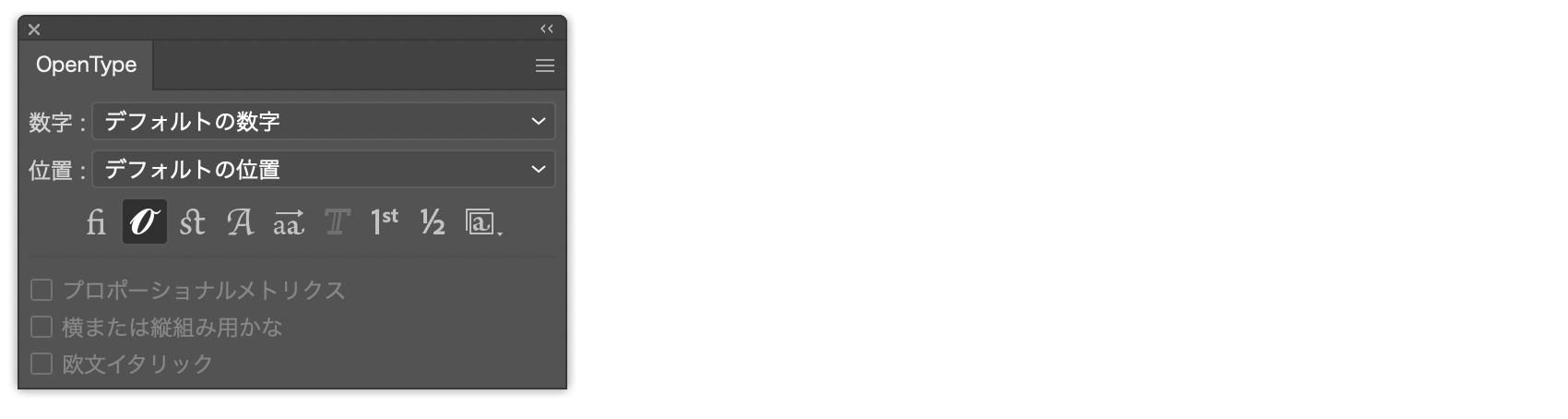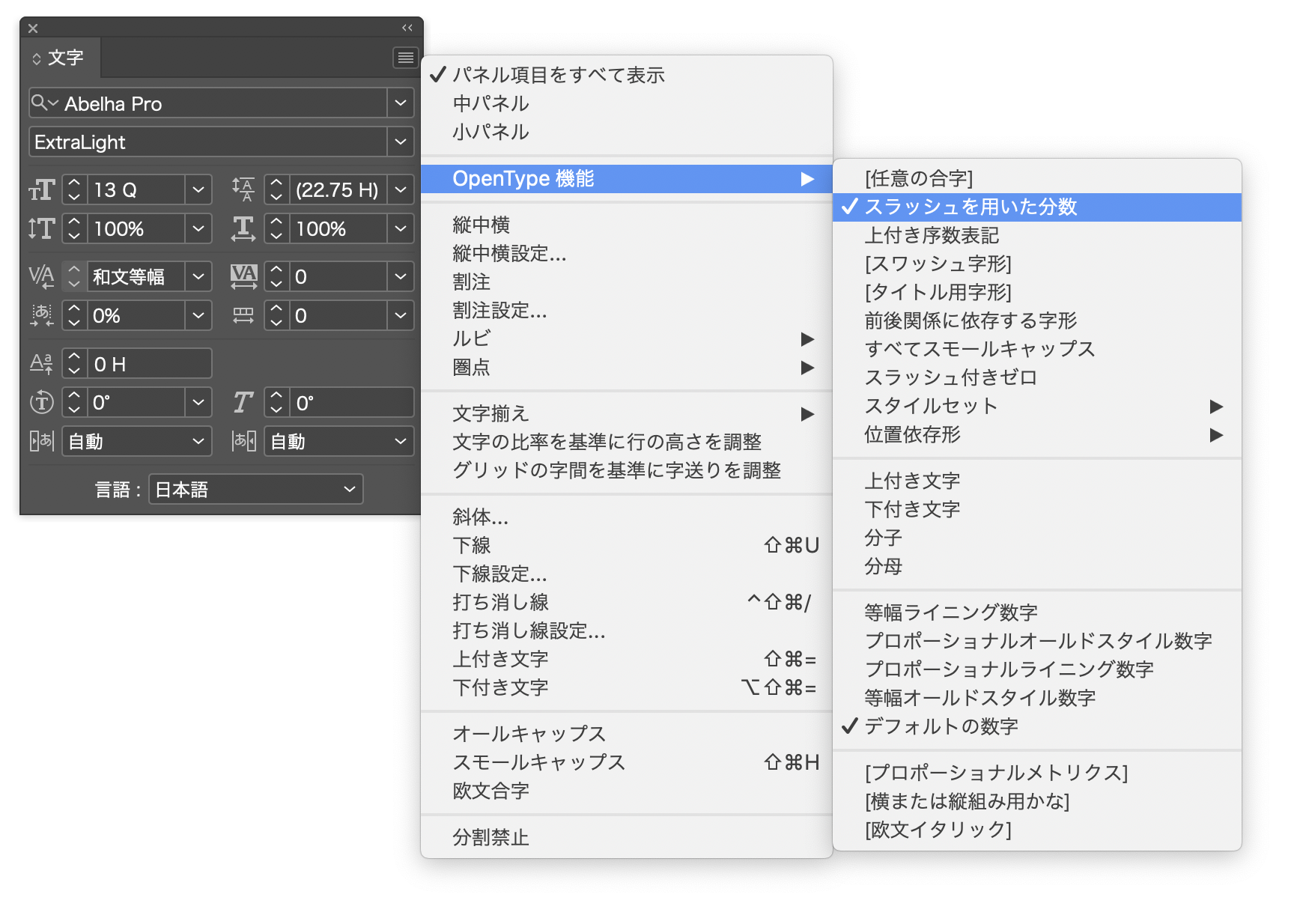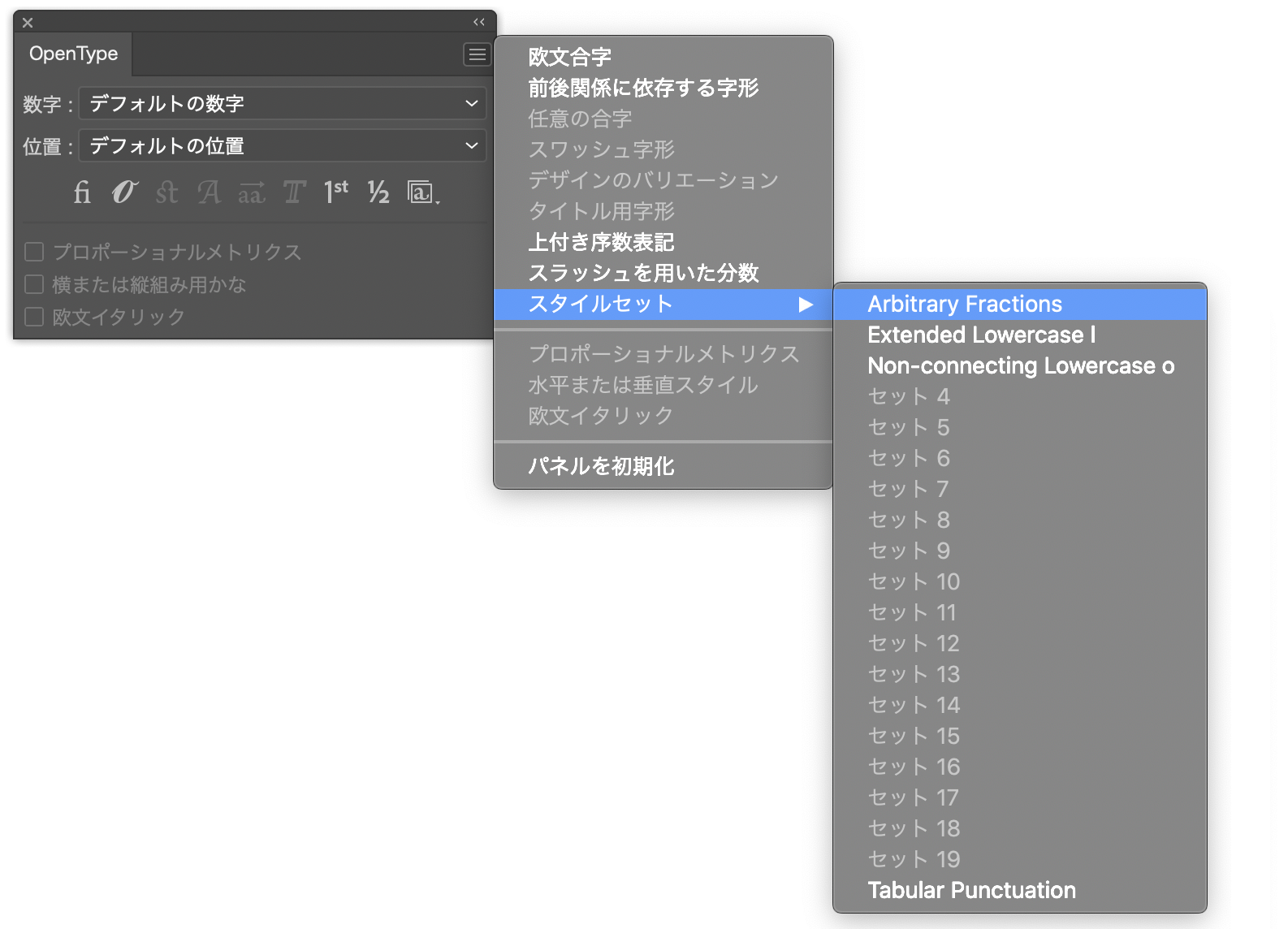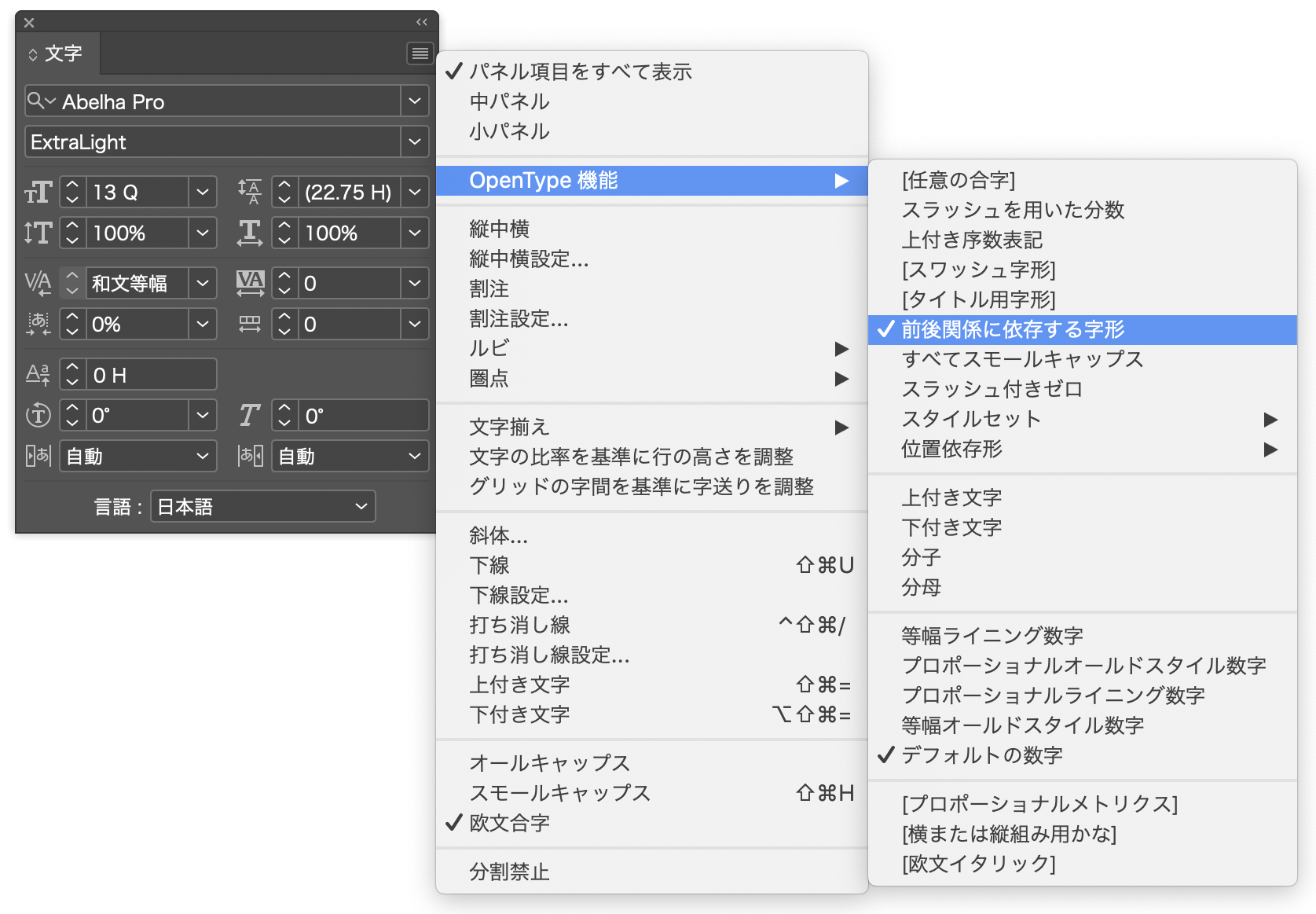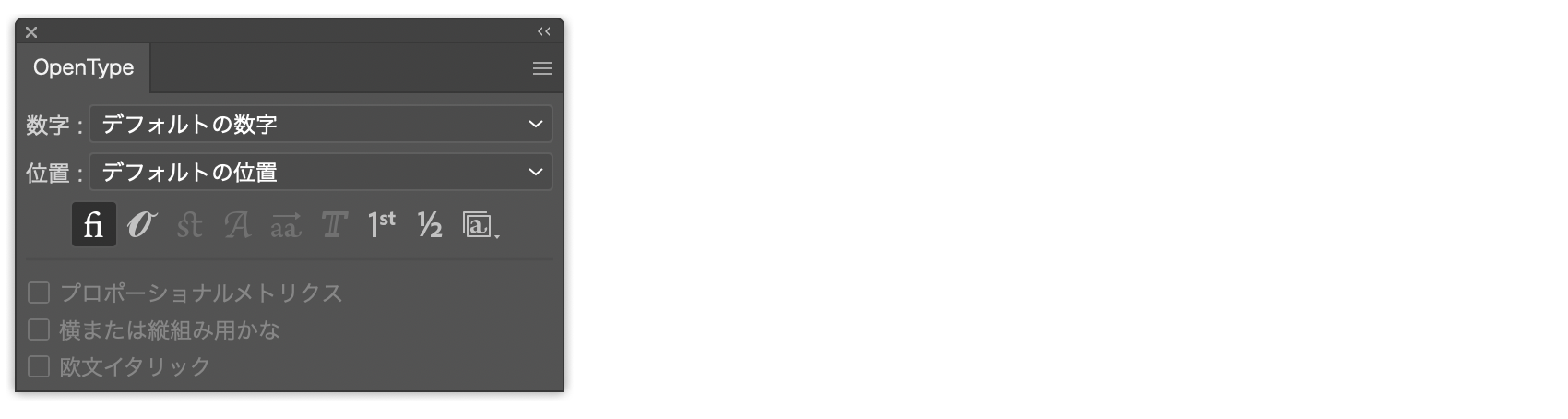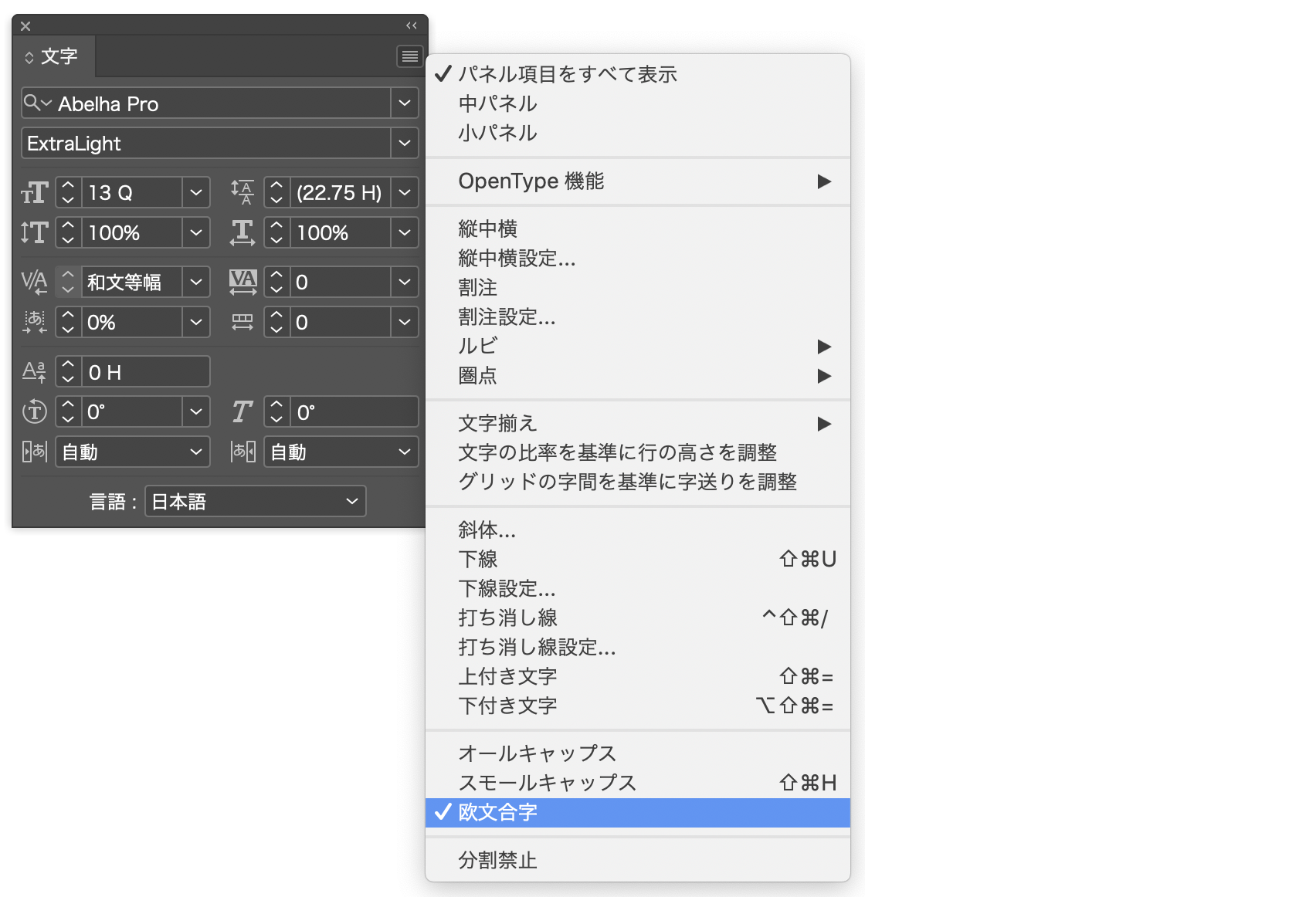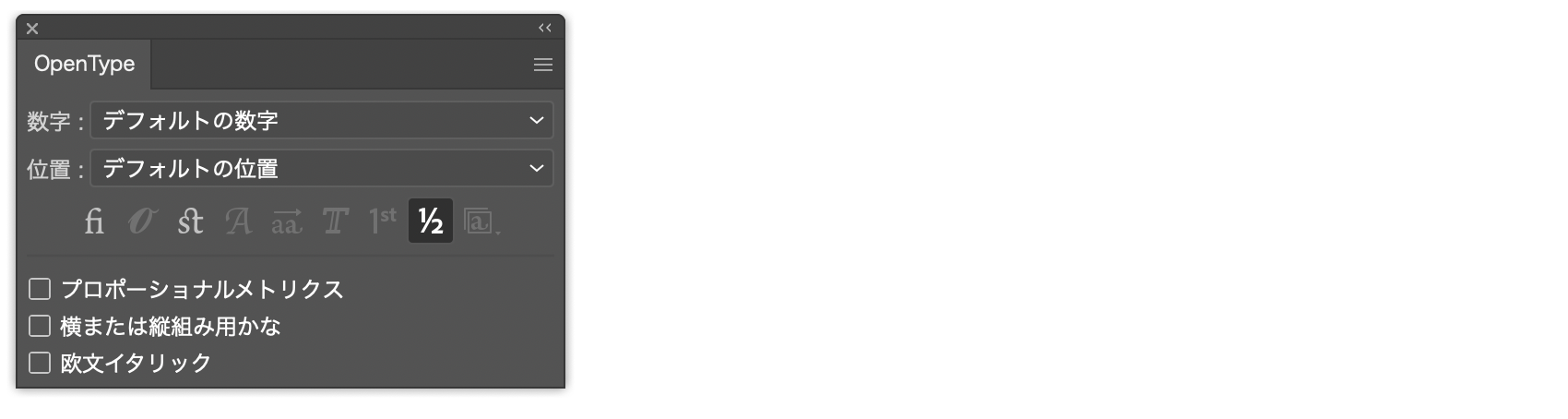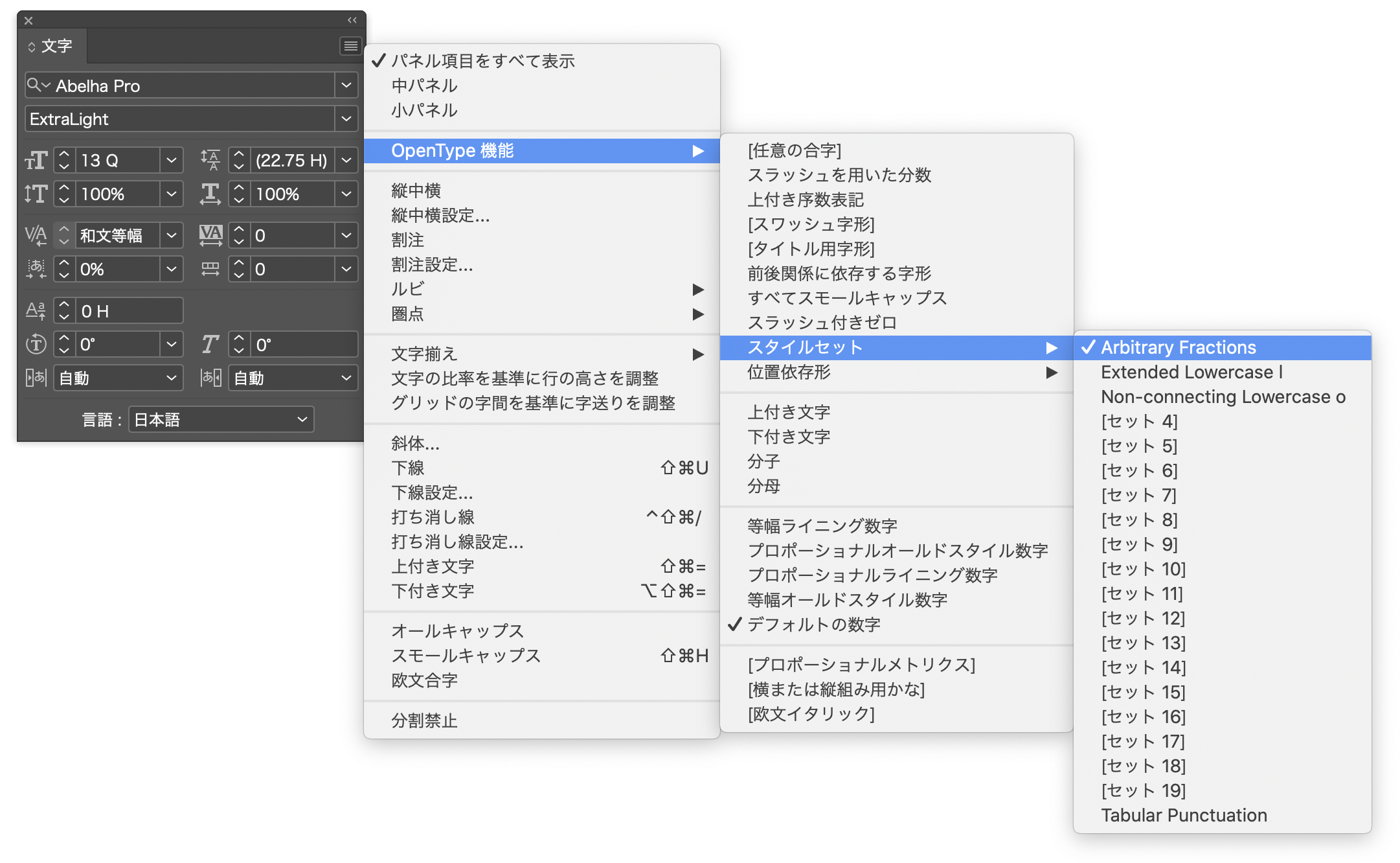
【Abelha Proの特徴】
Abelha Proは書簡の筆跡に着想を得てデザインされたスクリプト体です。可読性の向上や手書きによる字形の揺れの再現を目的として、さまざまな代替字形(オルタネイト)が用意されています。OpenType機能を通じてこれらの字形にアクセスすることで流れるような筆記体の雰囲気を演出することができます。
【Abelha Proの機能と使い方】
Abelha Proは以下のような機能を備えています。
(1)前後関係に依存する字形
語頭をはじめとする文中での位置や隣り合った文字によって、適切なスタイルの字形を呼び出します。多くのアプリケーションはこの機能をデフォルトで有効にしています。
(2)欧文合字
一般的な書体で搭載している "fi" や "fl" といった合字に加え、多数の合字を呼び出します。多くのアプリケーションはこの機能をデフォルトで有効にしています。
(3)スラッシュを用いた分数
分子と分母を水平の罫線で区切る「やぐら組」と呼ばれるデザインの分数を呼び出します。
(4)スタイルセット
a. Arbitrary Fractions
任意の数字の組み合わせの分数を、分子と分母の間にスラッシュを挟むスタイルで表現します。
b. Extended Lowercase l
アセンダの長い小文字のlを呼び出します。
c. Non-connecting Lowercase o
次の文字へと向かうストロークが見えない小文字のoを呼び出します。